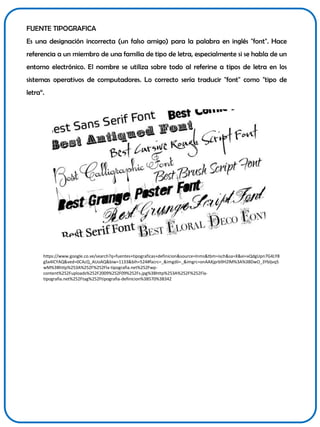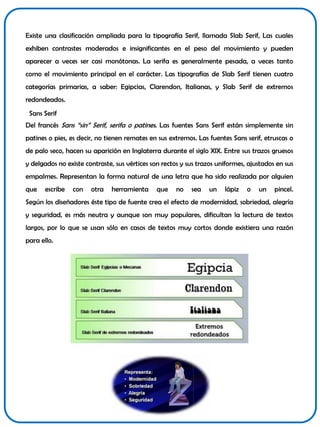
TIPOGRAFÍA
DEFINICIÓN
La Tipografía es la forma gráfica de expresar el lenguaje. Se puede ver como el arte y técnica
del manejo y selección de tipos, originalmente de plomo, para crear trabajos de impresión. El
tipógrafo Stanley Morison lo definió como:
Arte de disponer correctamente el material de imprimir, de acuerdo con un propósito
específico: el de colocar las letras, repartir el espacio y organizar los tipos con vistas a prestar al
lector la máxima ayuda para la comprensión del texto escrito verbalmente. Stanley Morison,
Principios fundamentales de la tipografía (1929)
ORIGEN DE LA TIPOGRAFIA
La tipografía (del griego τύπος typos, golpe o huella, y γράφω graphο, escribir) es el arte y
técnica del manejo y selección de tipos, originalmente de plomo, para crear trabajos de
impresión. La tipografía es el oficio que trata el tema de las letras, números y símbolos de
un texto impreso (ya sea sobre un medio físico o electromagnético), tales como su diseño,
su forma, su tamaño y las relaciones visuales que se establecen entre ellos. Definimos la
tipografía como el arte o técnica de reproducir la comunicación mediante la palabra
impresa, transmitir con cierta habilidad, elegancia y eficacia, las palabras. La tipografía es
el reflejo de una época. Por ello la evolución del diseño de las mismas responde a
proyecciones tecnológicas y artísticas. El signo tipográfico se ha considerado como uno de
los miembros más activos de los cambios culturales del hombre. En los primeros signos de
escritura, cada signo nos expresa una idea, un concepto o una cosa; estos signos se
combinan entre sí para comunicar ideas más complejas. Estos sistemas de escritura son los
pictogramáticos, jeroglíficos e ideogramáticos. El campo tipográfico, abarca la realización
de libros, periódicos, anuncios publicitarios, revistas, etc... y cualquier otro documento
impreso que se comunique con otros mediante palabras El tipógrafo Stanley Morison la
definió como: “Arte de disponer correctamente el material de imprimir, de acuerdo con un
propósito específico: el de colocar las letras, repartir el espacio y organizar los tipos con
vistas a prestar al lector la máxima ayuda para la comprensión del texto.” (1929)
ANATOMIA DEL TIPO
Este término hace referencia a la proporción que mantienen las letras, sin embargo no
hay que olvidar que existe una variante y una similitud entre todas las familias
tipográficas.
Los dos elementos principales en la constitución de una letra son las ASTAS y los REMATES.
Respecto a los contornos, encontramos internos o externos. Entre las partes de las letras se
encuentran los brazos, la cabeza, los remates y la cola.
Respecto a la alineación, se puede explicar de la siguiente manera:
El QUADRATIN es la caja de construcción de la letra. Es una medida tipográfica que
equivale a un cuadrado perfecto; la M es la que se adapta de manera perfecta a esta
medida.
Podemos usar el quadratín para la construcción de las letras teniendo en cuenta:
•M = Q
•V,Y,A = Q - 1a Caracteres abiertos
•W = Q + 2a
•B,D,H,K,N,P,R,T,U,X,Z = Q - 2a Letras regulares
•I = 1a
•C,G,Q,O,S,J,U = Q + 1/12a
•E,F,S,J,L = Q - 2 1/2a
Q = 1 Quadratín
a = asta
Para usar el quadratín en la construcción de las letras de caja baja, se hace de la siguiente
manera:
Los términos de CAJA ALTA y CAJA BAJA se originaron al inicio del desarrollo de la
tipografía, cuando tenían a cada letra individual y guardaban las mayúsculas o de caja
alta en la parte superior y las minúsculas o de caja baja en la parte inferior.
La parte superior de la letra Ñ se llama gurilla.
FUENTES Y FAMILIAS TIPOGRAFICAS
Se entiende por fuente tipográfica al estilo o apariencia de un grupo completo de caracteres,
números y signos, regidos por características comunes. Mientras que familia tipográfica, es un
conjunto de tipos basado en una misma fuente con algunas variaciones, tales como por
ejemplo, el grosor y la anchura, pero manteniendo características comunes. Los miembros que
integran una familia se parecen entre sí pero tienen rasgos propios. Cada fuente y familia
tipográfica tiene características que la distinguen entre otras, que las hace únicas y le da
personalidad al texto. Esa personalidad se magnifica cuando una fuente se usa a través de una
presentación digital. Antes de hablar sobre las características y usos de la tipografía
TIPOGRAFÍA DEL SIGLOXX Examina los principales aspectos que han dado forma a la historia del diseño tipográfico y, en los últimos tiempos, también del diseño gráfico. El libro muestra de qué modo las actuales corrientes tipográficas forman parte de un continuo proceso de cambio que se va tejiendo a lo largo de las diferentes décadas. Entre los temas tratados se encuentran la llegada de la producción de masas, el surgimiento de la figura del director de arte, la aparición de la retícula (y su posterior abandono), la llegada de los medios no impresos y el lanzamiento de los Macintosh, con la consiguiente aparición de una nueva generación de diseñadores que han visto cómo la tecnología digital facilita su modo de trabajo. En la década de 1990 la tecnología digital dio origen a una revolución en el diseño gráfico y en la práctica tipográfica. Esta edición revisada del clásico estudio de Lewis Blackwell actualiza la historia analizando los principales avances introducidos por la revolución digital. Entre otros puntos, Blackwell examina el desarrollo de tipos para pantalla y otras innovaciones relacionadas con la aparición de Internet como un nuevo medio global. No obstante, el autor expone en la introducción algunos de los retos a los que se enfrentan los diseñadores tipográficos y los usuarios en el nuevo milenio, dado que también existen aspectos negativos en las condiciones en las que los diseñadores trabajan actualmente. Además de contar con más de 300 ilustraciones, el libro reflexiona sobre la cultura de la experimentación en el diseño tipográfico contemporáneo y presenta de forma clara su contexto histórico. Por todo ello, la presente obra proporciona a los diseñadores, estudiantes y al público en general una guía completa y de fácil comprensión sobre la tipografía del siglo XX y las cuestiones fundamentales que condicionarán la práctica tipográfica en el futuro.